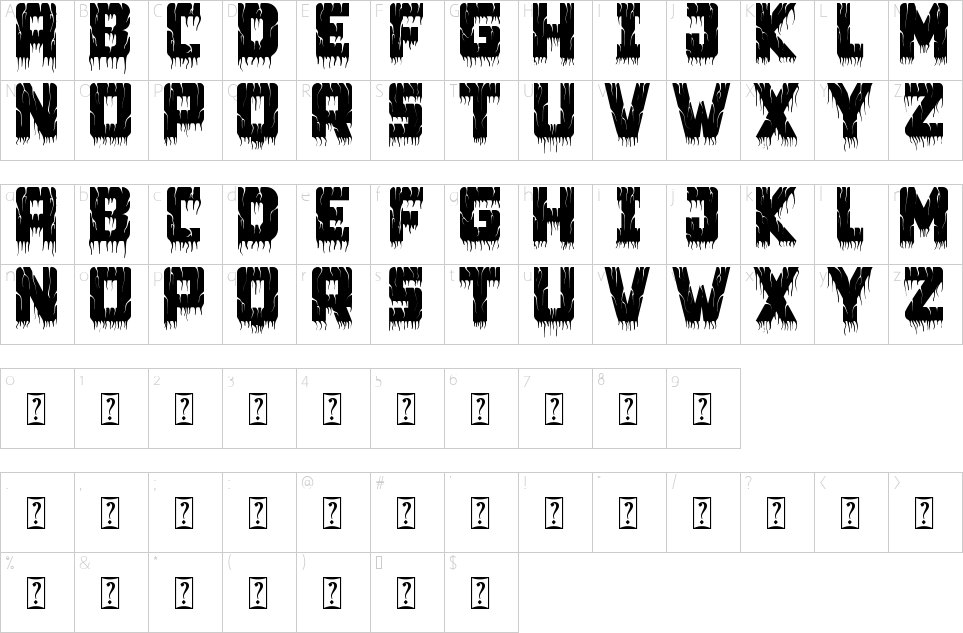
A fonte Spooky Grave é uma opção única para criar designs sobrenaturais e assustadores, perfeita para aplicativos especializados no Halloween ou em temas góticos. Desenhada pelo artista desconhecido Thomas Aradea, a fonte Spooky Grave já foi baixada 1.759 vezes e traz um ar de sombreamento que se adaptará bem ao seu projeto. Seja para criar grafismos espelhantes ou texturas assustadoras, Spooky Grave é uma escolha versátil que não decepciona. Para usuários de sistemas operacionais Windows e Mac, a fonte Spooky Grave está disponível gratuitamente para download. A experiência de uso é simples e intuitiva, permitindo que você personalize suas criações e introduza um toque único à sua produção com essa fonte única. Seja você um designer profissional ou iniciante, não hesite em experimentar esta font, pois certamente encaixará bem em seu próximo projeto assustador ou sobrenatural.